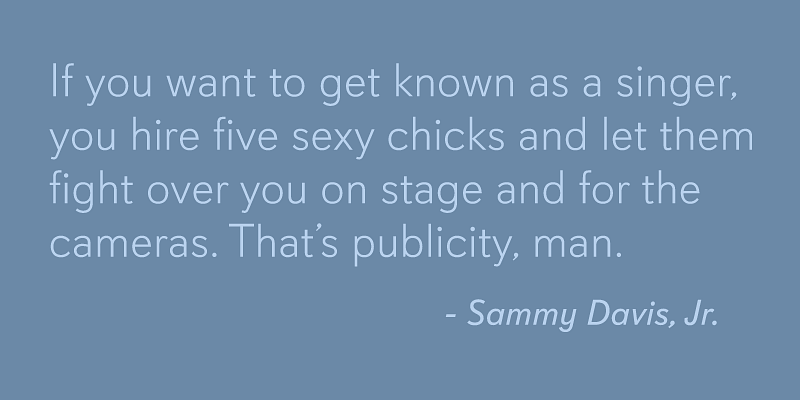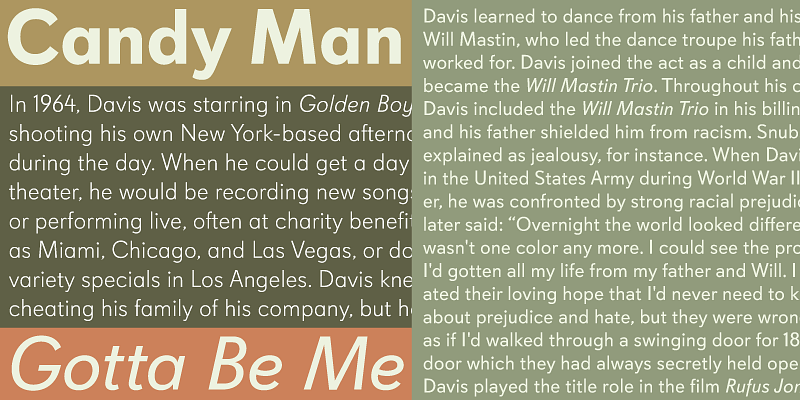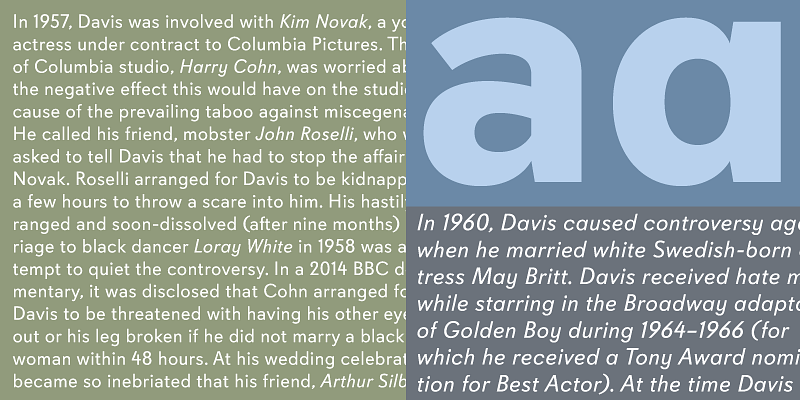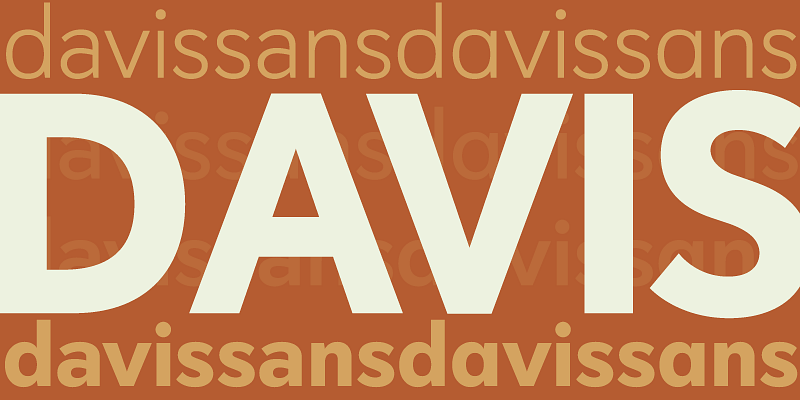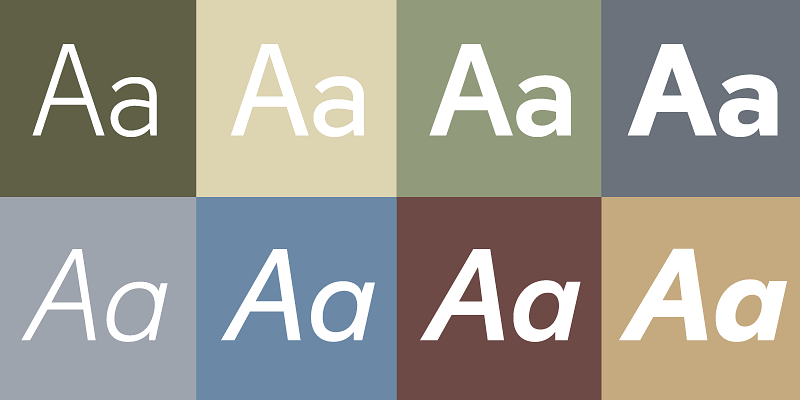
Davis Sans e la sua controparte slab serif, Davis, lavorano molto bene insieme per soddisfare i molteplici livelli di applicazioni aziendali, pubblicitarie e di interfaccia, dall’identità e dall’editoriale ai molti livelli di branding del prodotto.